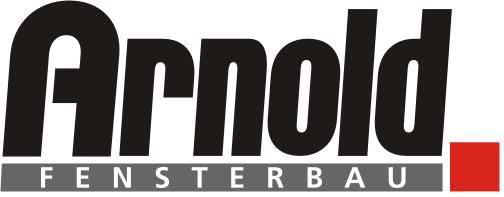
ich bräuchte mal wieder Eure Hilfe. Könnt Ihr mir sagen um welche Schriften es sich hier handelt?
Arnold ist wahrscheinlich selbstgebastelt. Die Blippo könnte Pate gestanden haben:
Arnold ist sicher mundgebissen, da passt ja gar nichts zusammen.
Jene könnte auch verwendet worden sein: